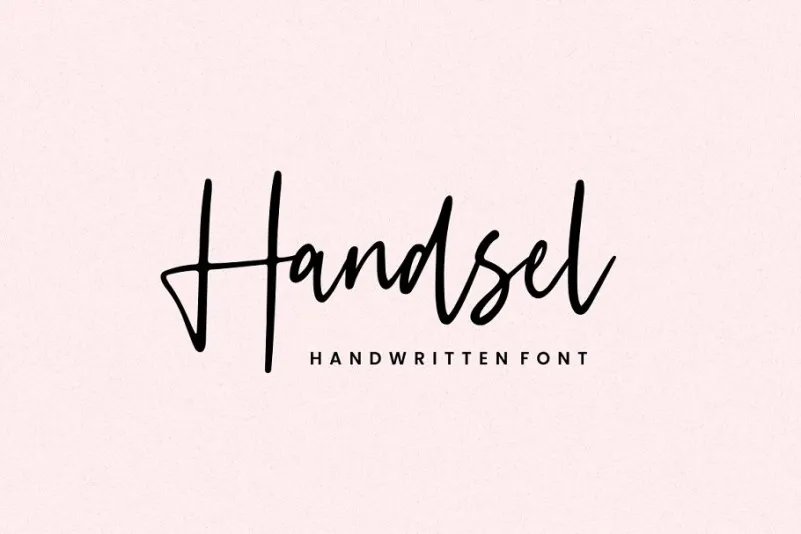
Handsel Script Font
Descubra a nova fonte ‘Handsel Script Font’, lançada pelo designer C00zona. Esta fonte é perfeitamente adaptada para uma variedade de projetos, desde identidades visuais e cartões de visita até embalagens de produtos e capas de livros. Com suas letras manuscritas naturais e modernas, a ‘Handsel Script Font’ oferece um toque autêntico e único a qualquer projeto. Seja para logotipos, convites ou embalagens personalizadas para eventos especiais, ela é uma escolha perfeita para adicionar originalidade ao seu design. Se você está procurando por uma fonte que seja tanto versátil quanto elegante, ‘Handsel Script Font’ é uma ótima opção. Suas linhas fluidas e escrita legível garantem que sua marca ou produto se destaque em meio aos demais, trazendo uma personalidade única para suas criações. Não perca tempo, adquira a sua hoje e transforme seu design no próximo grande hit!